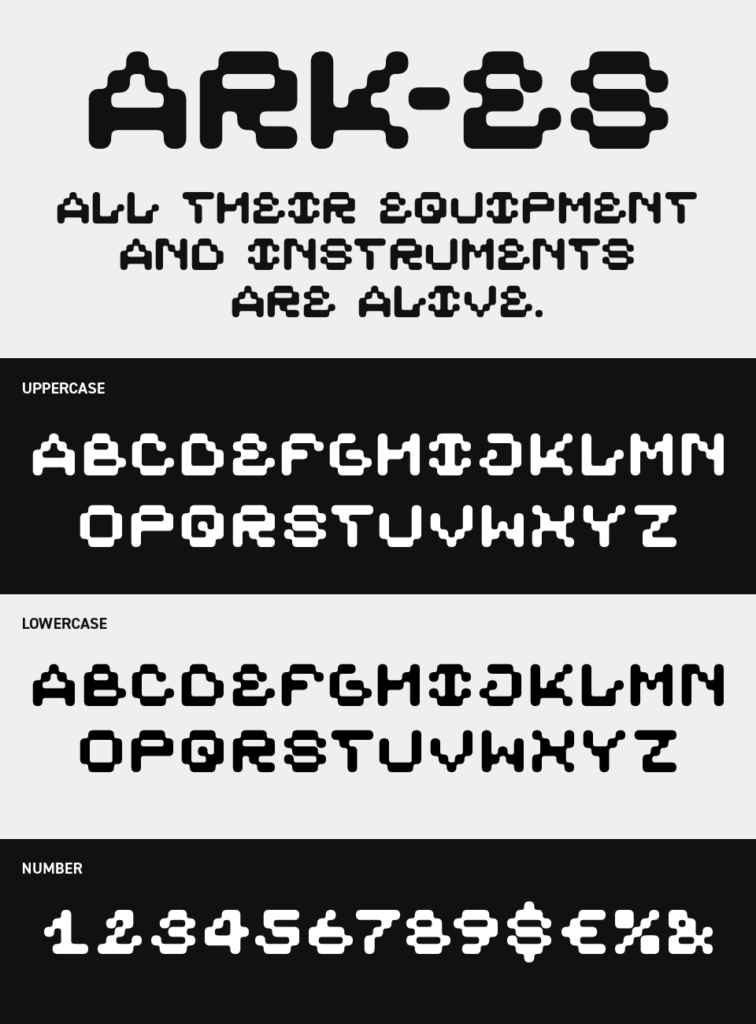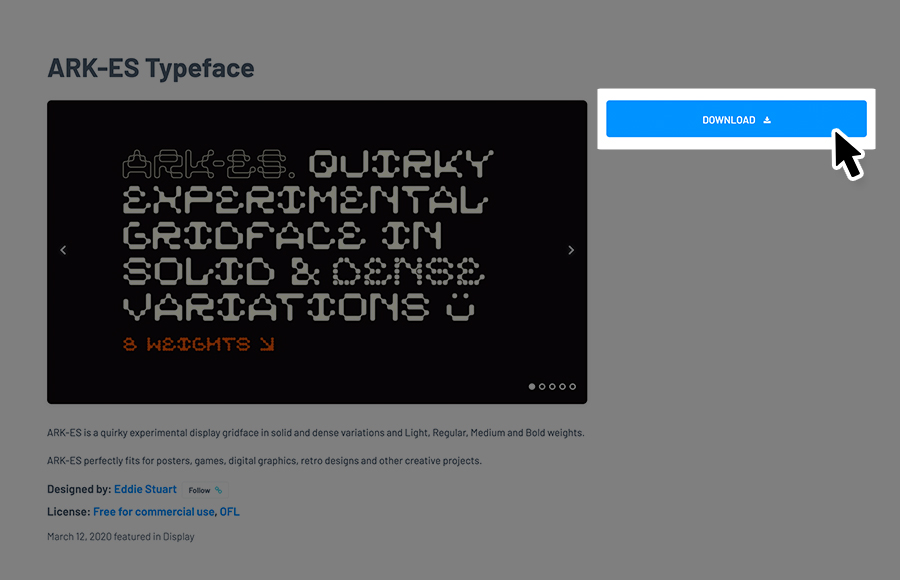
ARK-ESフォントは、ピクセルを感じるブロック状のパーツで構成されたデジタル感あふれるデザインフォントです。
角ばったピクセルが連結して作られるデザインが、レトロゲームや近未来的なUIを連想させ、画面上で強い視覚的インパクトを放つユニークな作りとなっているフォントです。
直線的で規則的なフォルムが特徴で、テック系のタイトルやゲームロゴ、SFテイストのビジュアルにぴったりなフォントです。サイズを大きく使うことでドットの存在感が際立つので、タイトルなどに取り入れるのがおすすめです。
収録文字は、大文字/数字/記号の収録となっています。